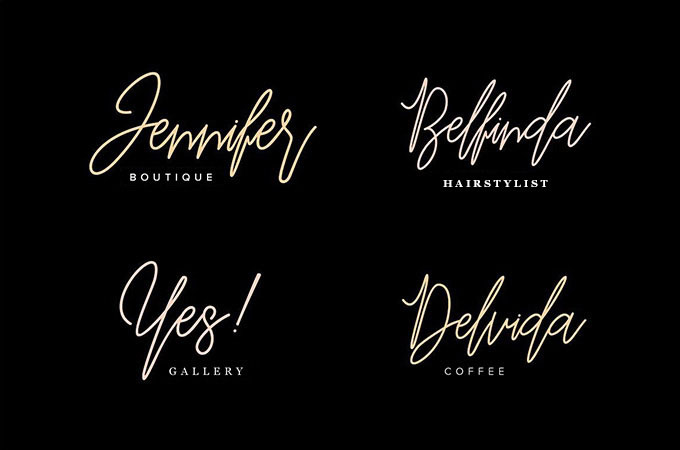
Befindisa: Font Tulisan Tangan yang Sederhana dan Elegan
Befindisa adalah font tulisan tangan yang memadukan kesederhanaan, gaya murni, dan kejelasan. Font ini dirancang untuk memberikan kesan yang elegan dan mudah dibaca dalam berbagai konteks desain.
Dengan bentuk huruf yang mengalir alami dan proporsi yang seimbang, Befindisa cocok digunakan untuk proyek-proyek kreatif seperti:
- Desain logo: Kesederhanaannya membuat Befindisa ideal untuk logo yang ingin tampil minimalis namun tetap berkesan.
- Undangan dan kartu ucapan: Gaya elegannya akan menambah nilai estetika pada undangan pernikahan, ulang tahun, atau acara spesial lainnya.
- Konten media sosial: Befindisa dapat digunakan untuk teks pada postingan Instagram, Facebook, atau platform media sosial lainnya agar terlihat lebih menarik dan personal.
- Desain grafis: Font ini dapat menjadi pilihan yang tepat untuk branding, ilustrasi, atau elemen desain visual lainnya yang membutuhkan sentuhan tangan yang lembut.
Dengan kombinasi kesederhanaan, gaya elegan, dan ketersediaan gratis, Befindisa menjadi pilihan font yang ideal bagi siapa pun yang mencari sentuhan personal dan profesional dalam desain mereka.
Befindisa is hand-letter script font combining simplicity, pure style and conciseness.